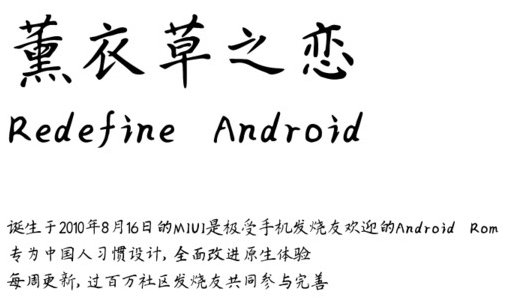
薰衣草之戀字體是出自思雨字體庫(kù)的一款簡(jiǎn)潔清新的手寫(xiě)字體,很有楷書(shū)字體的約為,筆畫(huà)端正而大氣,快來(lái)綠色資源網(wǎng)試試吧!
薰衣草字體出自思雨字庫(kù),是一款效果十分出色的手寫(xiě)字體,給人端正而不失大方、綿柔而不失剛硬的視覺(jué)美感,讓你的藝術(shù)設(shè)計(jì)、包裝設(shè)計(jì)更加出彩!